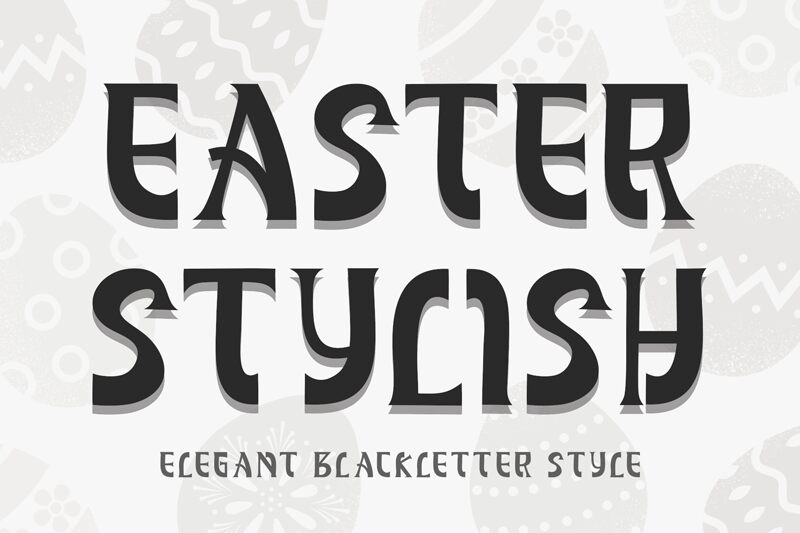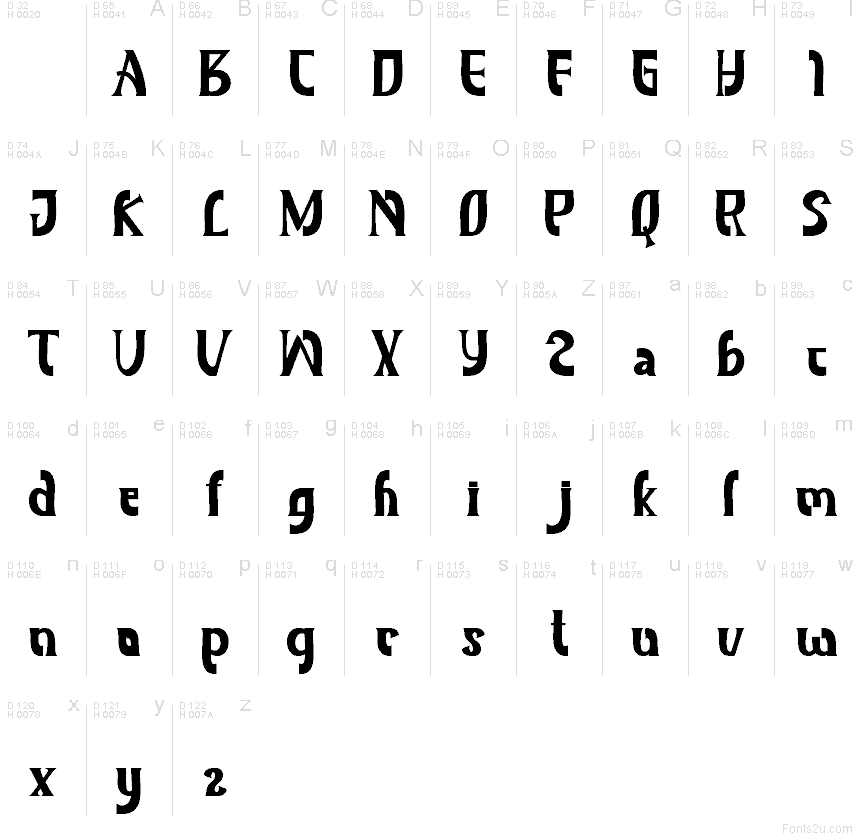
Easter Stylish
A Easter Stylish, da Yoga Letter, é uma fonte display gratuita para a Páscoa com um toque de banda desenhada, lembrando recortes de papel, que mistura curvas arredondadas com arestas retas e marcantes. O desenho das letras é particularmente distinto na fluidez do S e no formato em degraus do E, dando ao conjunto um ritmo artesanal e cartazista, sem nunca se tornar excessivamente decorativo.
A Easter Stylish funciona muito bem em cartões de Páscoa, folhetos sazonais, marcas de artesanato, convites de festas, projetos infantis e gráficos criativos para redes sociais, pois as suas formas transmitem claramente o tema festivo sem necessidade de adornos extras. Esta fonte gratuita também é perfeita para logotipos curtos, etiquetas de produtos, banners de eventos e títulos alegres onde uma fonte temática precisa de se destacar por si só.